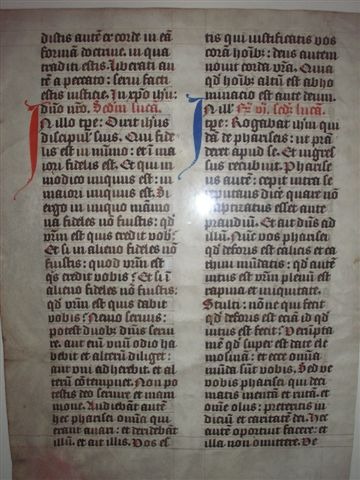
Gutenberg Textur
Ich habe eine Frage zur Schrift der Gutenbergs Bibel 42, und zwar warum hat sich Gutenberg ausgerechnet für Textur als Vorbild der Schrift für seine Bibel entschieden und mit welchen Techniken hat er die Handschrift nachgeahmt?
Bei Wiki findet man schon etwas zu der Schriftwahl und den Vorlagen. Wie er das genau technisch nachempfunden hat, also, ob er die Buchstaben selber erst geschrieben oder gleich von den Vorlagen abgezeichnet weiß ich jetzt nicht und das kann man da auch nicht rauslesen.
Ich nehme an, daß Gutenberg die Textura einfach deshalb verwendet hat, weil sie die damals übliche Schrift war. Er hat ja zunächst erst einmal »nur« eine neue Technik erfunden, nicht eine neue Ästhetik. Ästhetisch hat er sich also einfach an die vorherige Technik — abschreiben der Bücher mit der Feder — angelehnt. Für die Feder war die Textura sehr praktisch, auch ist sie platzsparend, was bei den damaligen Kosten für Papier und besonders für Pergament ein wichtiges Argument war.
Wahrscheinlich war die Textura für Gutenberg auch deshalb gut geeignet, weil sie einfache Strukturen und kräftige Formen hat. Das war sicher sowohl für den Schriftguß selbst als auch für das Schneiden der Gießformen ein Vorteil. Das ganze war ja noch keine lange ausgereifte Technik, sondern es gab sicherlich zunächst Anfangsschwierigkeiten zu überwinden; dies wäre mit einer komplexeren Typographie wahrscheinlich noch schwieriger gewesen. Das selbe gilt sinngemäß für den Druck: Die einfachen, robusten Formen haben sicher relativ wenig Probleme bereitet; immerhin hatte man ja noch keine feinmechanischen Hochleistungspressen sondern eine umgebaute Weinpresse aus Holz mit den entsprechenden Materialtoleranzen.
Vielleicht soll man auch versuchen festzustellen, wie unterscheidet sich die Textur von Gutenberg von der Handschrift Textur? Was hat er zur Entwicklund dieser Schrift beigetragen? hat er überhaupt was beigetragen?
Er hat ja zunächst erst einmal »nur« eine neue Technik erfunden, nicht eine neue Ästhetik. Ästhetisch hat er sich also einfach an die vorherige Technik — abschreiben der Bücher mit der Feder — angelehnt.
Er hat ja mit den über 290 Glyphen versucht die damalige Handschrift nach zu ahmen, um nicht zu modern und technisch daherzukommen und, um die entsprechende Wertigkeit darzustellen.
"..Gutenberg had prepared a large set of abbreviations and ligatures that
could be used to replace certain words or combinations of letters. Apart from that, a
letter in his composition could be typeset using several variants of a glyph with different
width, depending on the requirements of typesetting a line. The alphabet used for
typesetting the Bible contained about 290 characters, many of them were ligatures and
multiple glyphs of certain characters. The main intention of use of multiple glyphs was
most likely to achieve the constant distance between the vertical strokes of characters.
The compositor therefore could select the glyph of a letter that seemed to be the best
variant according to the position of the letter in the word or the line. The result is the
“woven” or “grid” appearance of pages with perfectly uniform greyness. The multiple
glyphs might also have been used for the adjustment of line width. However, this seems
to be a minor effect..."
Hat jemand noch eine Idee was das genau für eine Schrift sein könnte, die Gutenberg als Vorbild genommen hat? Ich meine, es gibt wahrscheinlich mehrere Varianten von Textur..
Hier habe ich ein Bild einer Handschrift aus der Zeit gefunden:
"..Insbesondere in Frankreich und Italien entstanden Bibeln in Miniaturschrift auf Jungfernpergament. Dazu gebrauchte man sehr dünnes Pergament aus den Häuten neugeborener (oder teilweise auch noch ungeborener) Lämmer und Zicklein.." :cry:
Hilfe! Wo kann ich ein Beispiel der Messalhandschrift des Meinzer Klosters aus dem 15 Jh finden?